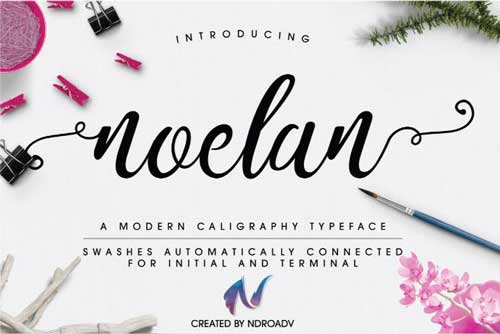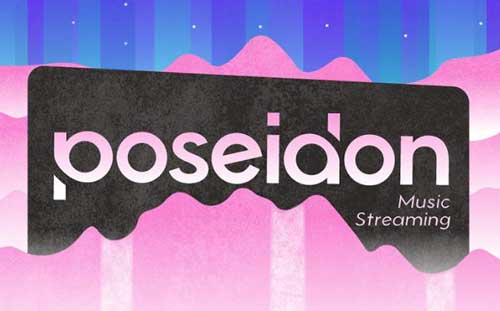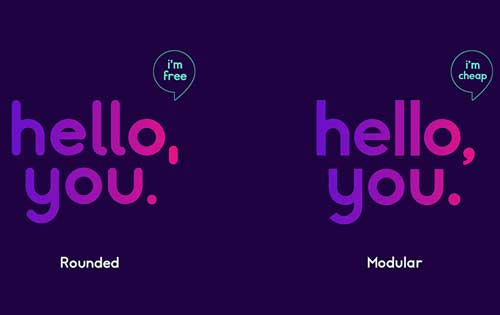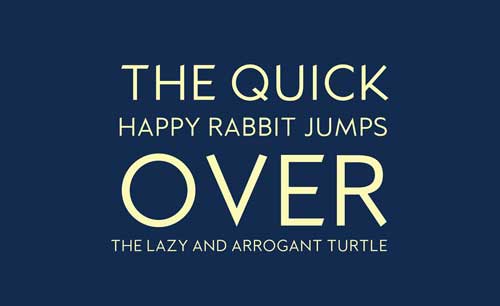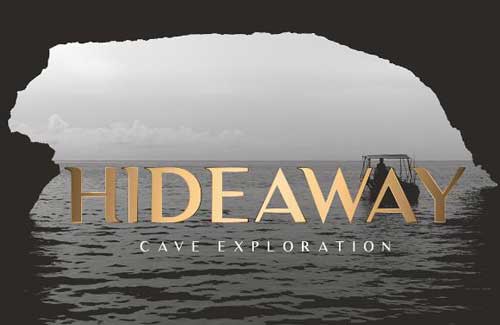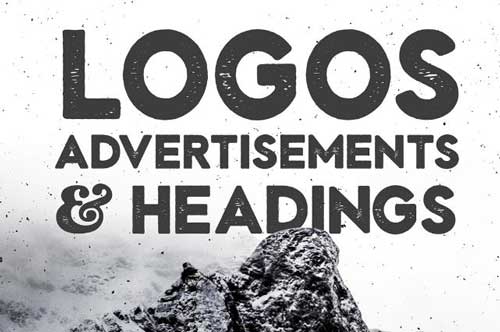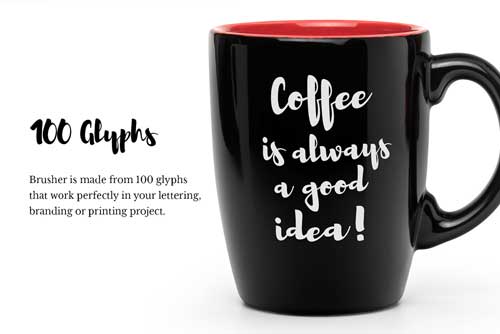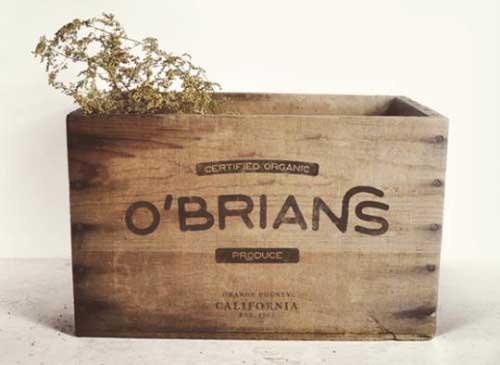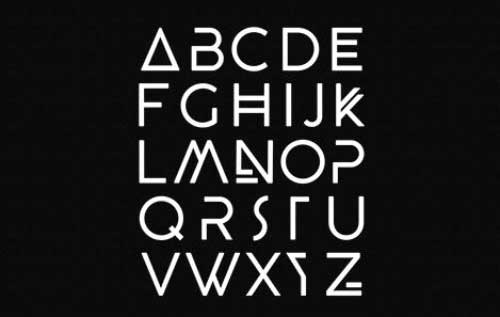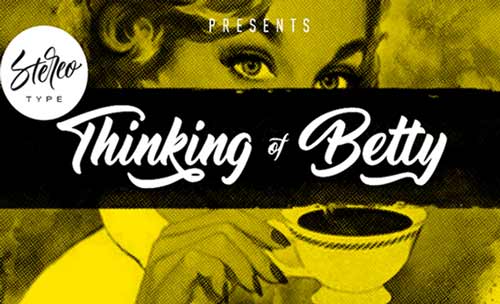
20 Font Keren Untuk Desain Grafis
Untuk para pecinta desain grafis, penggunaan font memang paling utama. karena font dapat memberikan ciri khas pada desain. contohnya desain baju kaos distro bertemakan tipografi, maka gunakanlah font yang keren agar kesannya menarik, berikan font terbaru supaya desain lebih terupdate. kumpulan font keren dibawah ini juga bisa dimanfaatkan untuk membuat logo dipadukan dengan bentuk. pokoknya tergantung imajinasi dan kreativitas sobat.
1. Font Noelan | Download Gratis
Font noelan memiliki bentuk seperti tulisan bersambung. bentuk lengkungannya mendakan keindahan, kecantikan. sangat cocok untuk desain feminim, desain bernuansa lembut dll.
2. Font Anurati | Download Gratis
Font yang memiliki nuansa ketajaman, nuansa harapan & keinginan pada bentuknya. kalau mau pakai jenis type face berikut, coba padukan dengan desain logo atau bertemakan harapan.
3. Font Shumi | Download Gratis
4. Font Somantic | Download Gratis
5. Rude | Download Gratis
Font rube salah satu font yang mempunyai simbol kejantanan.
6. Font Brusher | Download Gratis
Salah satu jenis font bush yang bisa sobat gunakan untuk desain grafis. bentuknya yang imut namun tetap elegan membuatnya cocok untuk desain tema apapun. sangat baik digunakan sebagai branding. contohnya mock up gelas mug dll.
7. Kano Typeface | Download
8. Font Terbaru Atami | Download
9. Sonder | Download Font
10. Luxia | Download Font
11. Elianto | Download
12. Shamery Font Sanserif Terbaik 2017 | Download
13. Beyno | Download Font
14. L-7 Stencil Font | Download
15. Old Growth | Download
16. SHKoder 1989 | Download
17. Porto | Download
18. Azedo | Download
19. Thinking Of Betty | Download
20. The Humber Font | Download Font Gratis
Nah itulah font font pilihan untuk proyek desain grafis sobat. semuanya memiliki karakteristik sendiri.